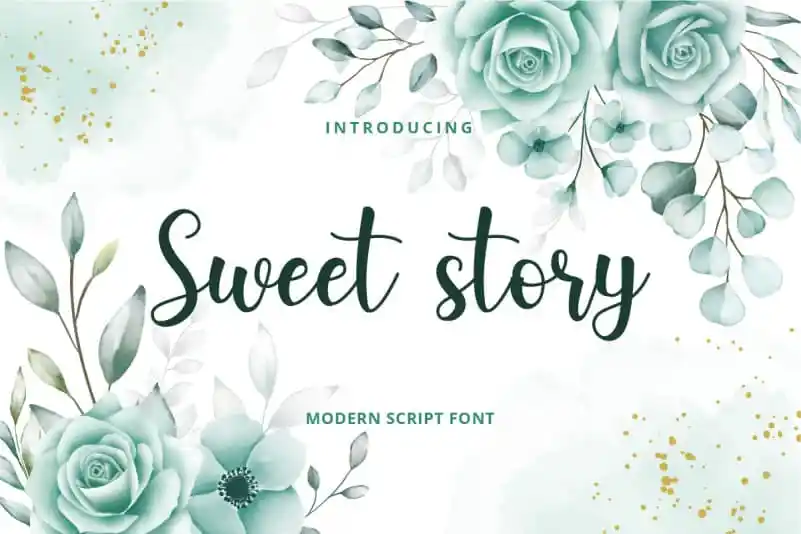
Sweet story Script Font – Download Grátis
A Sweet Story Script Font é uma elegante fónt que transmite delicadeza e elegância através de sua escrita manuscrita fluida. Com caracteres belos e bem equilibrados, ela se adapta a um amplo número de projetos. Inclua essa fonte em seus ideias criativas mais audaciosas e observe como ela as torna vibrantes e únicas. Esta escolha certamente adicionará profundidade aos teus trabalhos design. Fornecida pela planetz studio, a Sweet Story Script Font se destaca no seu nicho de fóntes manuscritas delicadas.